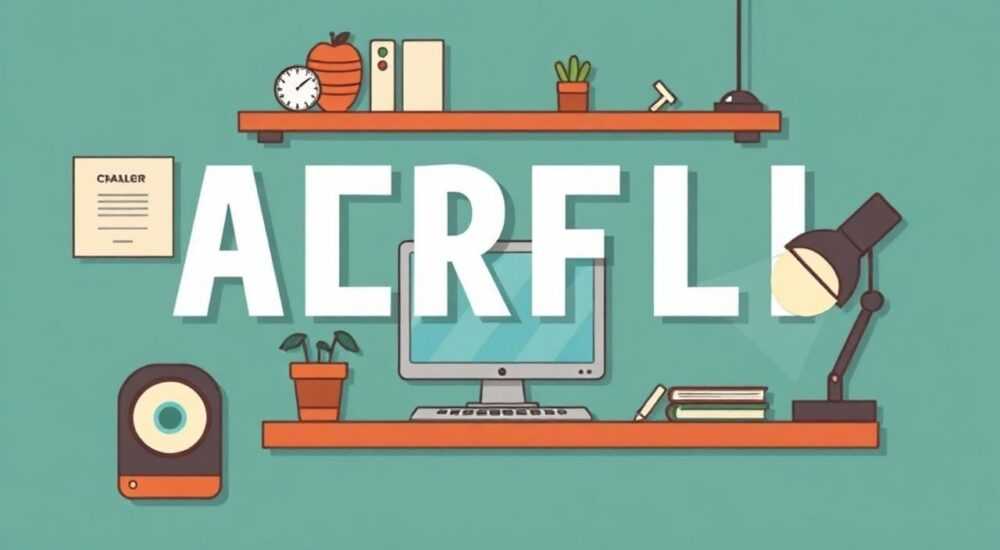
Шрифт лофт
Шрифт лофт стал неотъемлемой частью современного дизайна, органично вписываясь в интерьеры и графические решения. Его популярность стремительно растет среди дизайнеров и архитекторов благодаря универсальности применения и четкому геометрическому почерку. Особенно интересно наблюдать, как этот стильный шрифт трансформируется из простого набора букв в полноценный элемент декора, способный задать тон всему пространству.
Что делает шрифт лофт особенным?
В современном мире визуальной коммуникации важно понимать, что отличает один шрифт от другого. Шрифты в стиле лофт привлекают внимание своей минималистичностью и строгой геометрией, но при этом сохраняют определенную теплоту и человечность. Интересно отметить, что именно эта особенность часто становится камнем преткновения для начинающих дизайнеров – найти правильный баланс между строгостью и уютом.
Чтобы лучше понять уникальность шрифта лофт, представьте себе старые промышленные здания с их грубой кирпичной кладкой и металлическими конструкциями. Так же и шрифт лофт сочетает в себе индустриальную основательность с современной элегантностью. В этой статье мы подробно разберем все аспекты его использования, от базовых принципов до профессиональных хитростей.
Основные характеристики шрифтов лофт
Рассмотрим ключевые параметры, которые определяют шрифты данного направления:
- Геометрическая точность и строгие линии
- Минималистичный дизайн без лишних элементов
- Четкие контуры и акцент на вертикалях
- Пространственная сбалансированность знаков
Особенно стоит отметить модульную структуру шрифта лофт. Каждый символ представляет собой законченную композицию, где каждая линия имеет свое функциональное назначение. Это особенно важно при работе с крупными надписями или вывесками.
Параметр |
Шрифт лофт |
Классический serif |
Толщина линий |
Равномерная |
Переменная |
Наличие засечек |
Отсутствуют |
Присутствуют |
Геометричность |
Умеренная |
Практическое применение шрифта лофт
Интересно, что возможности применения шрифтов лофт значительно шире, чем может показаться на первый взгляд. От масштабных архитектурных решений до небольших деталей интерьера – этот шрифт универсален. Особенно эффективен он в создании фирменного стиля заведений, работающих в лофт-направлении.
Разберем конкретные примеры:
- Меню ресторанов и кафе
- Навигационные системы торговых центров
- Декоративные элементы интерьера
- Рекламные материалы
При работе с шрифтом лофт важно учитывать несколько ключевых моментов:
- Расстояние между буквами (кернинг)
- Соотношение высоты символов к их ширине
- Цветовые контрасты
- Масштабирование
Пошаговое руководство по созданию композиции
Давайте рассмотрим практический пример создания композиции с использованием шрифта лофт:
- Определите основное сообщение и его место в пространстве
- Выберите подходящий вариант шрифта из доступных семейств
- Настройте базовые параметры: размер, межбуквенное расстояние, цвет
- Добавьте необходимые графические элементы
- Проверьте читаемость с разных дистанций
Важно помнить о правилах визуального восприятия. Человеческий глаз лучше воспринимает информацию, когда она организована по принципу «золотого сечения». Поэтому при размещении текста старайтесь соблюдать эти пропорции.
Сравнительный анализ популярных вариантов
Существует множество реализаций шрифтов лофт, каждая со своими особенностями. Рассмотрим наиболее популярные варианты:
Название |
Лучше всего подходит для |
Loft Sans |
Минималистичный, четкий |
Навигация, вывески |
Urban Loft |
Более мягкие формы |
Меню, реклама |
Industrial Sans |
Акцент на геометрию |
Декор стен |
Александр Петров, арт-директор дизайн-студии «Modern Vision» с 15-летним опытом в создании брендированных пространств, делится своими наблюдениями:
«За годы работы я заметил интересную тенденцию – шрифты лофт особенно эффективны в комбинации с натуральными материалами. Например, металлические буквы на кирпичной стене создают потрясающий эффект. Важно помнить о правильном освещении – оно может как подчеркнуть достоинства шрифта, так и испортить всю композицию.»
В своей практике Александр часто использует технику многослойного размещения текста, когда основной шрифт дополняется фоновым слоем другого цвета. Это создает дополнительную глубину и объем.
Частые вопросы и ответы
- Как правильно выбрать размер шрифта?
Все зависит от дистанции просмотра. Для меню оптимальный размер – 20-30 мм высотой, для вывесок – от 50 мм и выше. При этом важно учитывать окружающее пространство и общую концепцию дизайна.
- Можно ли использовать шрифт лофт в классических интерьерах?
Да, но с осторожностью. Лучше выбирать более мягкие варианты и комбинировать их с классическими элементами декора.
- Какие материалы лучше всего подходят?
Металл, дерево и стекло – традиционные материалы для воплощения шрифта лофт. Однако современные технологии позволяют успешно использовать и другие варианты, например, акриловое стекло или композитные материалы.